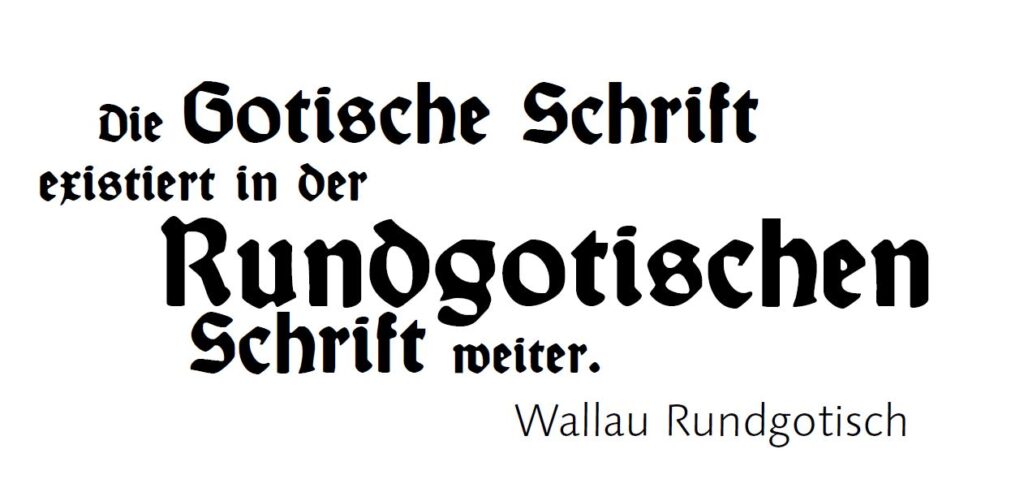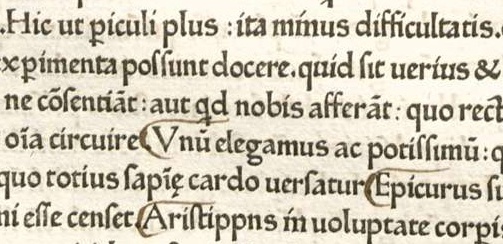
13.–14. Jh.
1200 und die hochgestreckte Gotik
Die Gotik bricht mit den Rundungen der Karolingischen Minuskel. Hochgestreckte Spitzbögen und scharfe Ecken prägen den Stil – in Architektur wie auch in der Schrift. Die Betonung der Vertikalen spiegelt den gotischen Kathedralbau wider und führt zu einer völlig neuen Schriftform: der Gotischen Schrift, Vorläuferin der gebrochenen Schriften.
Gutenberg nutzte später die Textura, eine Variante der Gotik, für seine berühmte 42-zeilige Bibel. Aus ihr entwickelten sich die Fraktur und die Schwabacher, die die deutsche Schriftgeschichte entscheidend prägten. Während die Schwabacher lange Zeit populär blieb, setzte sich schließlich durch Luthers Bibelübersetzung die Fraktur durch.
1400 und der Beginn der Renaissance
Mit der Renaissance begann die bewusste Rückbesinnung auf die Antike. Um 1400 schufen italienische Mönche in der Frührenaissance die Humanistische Minuskel, auch Antiqua genannt. Sie verband das Großbuchstabenalphabet der Römischen Kapitalis mit dem Kleinbuchstabenalphabet der Karolingischen Minuskel – erstmals wurden beide Alphabete klar unterschieden.
Parallel entstand die Humanistische Kursive, veröffentlicht 1423 von Niccolò Niccoli. Die Gotische Schrift lebte jedoch in der Rundgotischen Schrift noch weiter.